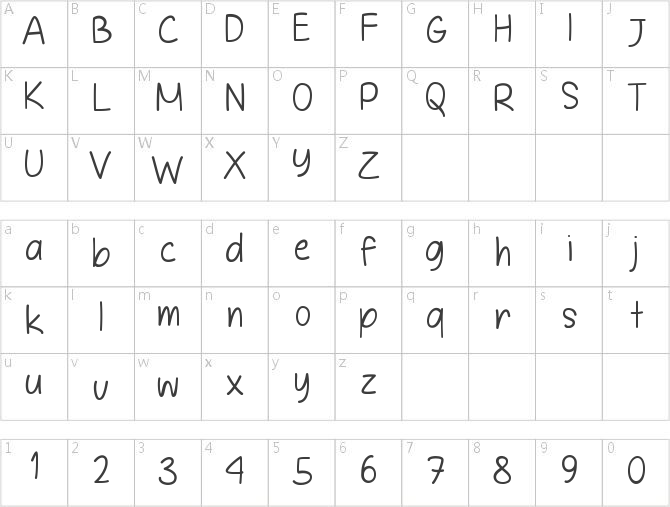
字體名稱: It is D
It is Definitely Possible - TTF
It is Definitely Possible - TTF字體字庫是一款讓人賞心悅目、百看不厭的英文字體,適合各類廣告和產品包裝設計應用,字體大小0.1MB,格式為ttf字體,上傳用戶是凡客,作者/版權方為未知